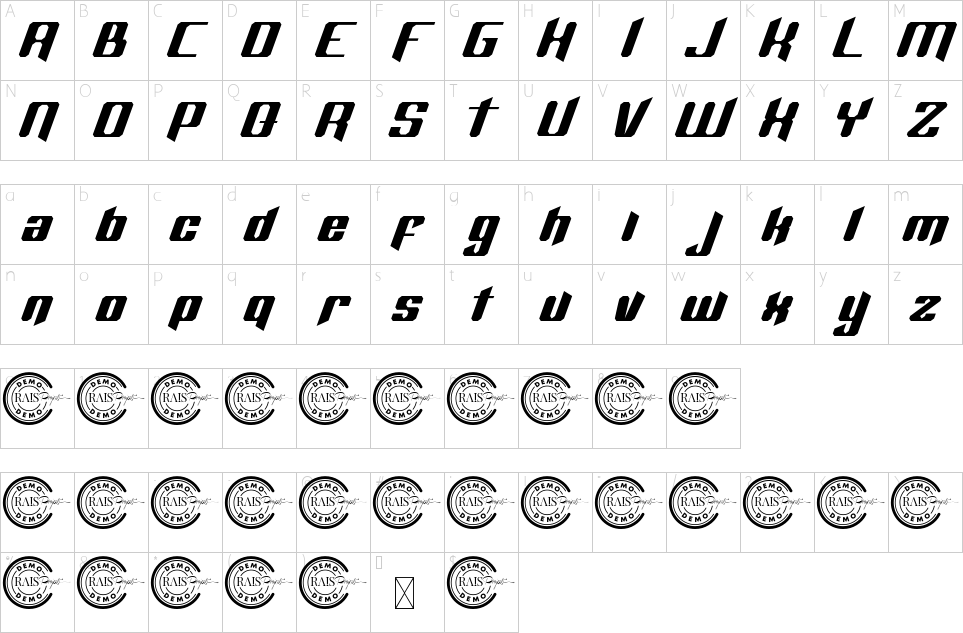
A Overtake Font é uma adição fresca à biblioteca de fuentes gratuitas disponíveis para download, criada por uma equipe desconhecida até agora. Seu design inovador e atemporal oferece uma versão para sistemas Windows e Mac. Com apenas 3,814 downloads registrados, essa fonte representa um equilíbrio entre estética elegante e função funcional. Os criadores da Overtake foram capazes de criar algo que combina modernidade com simplicidade, tornando-a uma opção versátil para designers digitais. Seja você um profissional ou iniciante, a Overtake pode fornecer aquele toque especial ao seu próximo projeto. Não perca tempo – é hora de dar vida à sua criatividade através desta fonte moderna e fácil de usar.